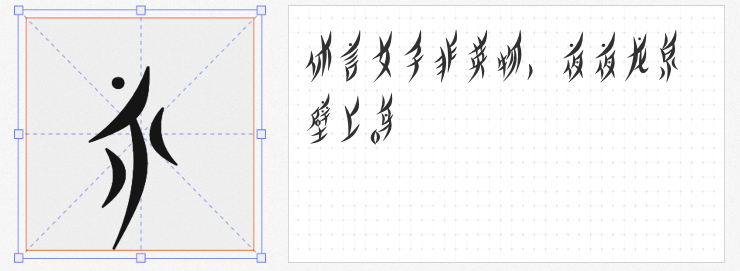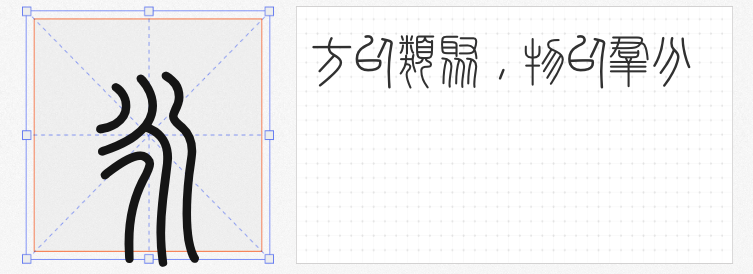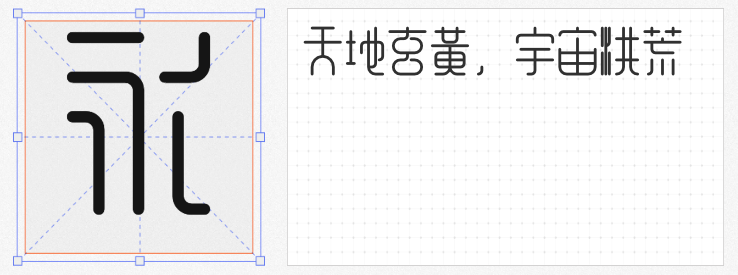
1. 余繁新语 Bold
这款字体以小篆为原型进行几何化重构,将婉转流畅的曲线转化为棱角分明的块面结构,粗细统一的笔画与夸张的负形切割形成强烈视觉张力。其“简而不失古韵”的设计哲学,既保留了篆书的仪式感,又通过简化结构适配现代排版需求。在电商促销海报中,它能以标题形式瞬间聚焦视线;在品牌标志设计中,其独特的文化符号属性更能传递历史厚重感,成为连接传统与当代的视觉桥梁。
2. 峄山碑篆体
通过高精度路径临摹技术,这款字体完整复现了秦代《峄山碑》的刀刻韵味,同时修复了千年风化导致的笔画残缺,让每个字符都呈现出金石铿锵的质感。设计团队以《说文解字》为部首规范基准,创造性地将篆书结构系统化,使非常用字也能保持统一的风格语言。在文化展览主视觉、国风产品包装等场景中,其严谨的考古级复刻精度,能为设计注入令人信服的历史真实感。
3. 也字工厂柳叶体
作为全球首款免费商用女书字体,也字工厂柳叶体以纤细飘逸的曲线重构女性专属文字符号,笔画如柳叶轻拂,既保留了原始女书“斜体弧形”的书写特征,又通过标准化处理提升多字符排版的和谐度。在女性主题公益海报、文创产品设计中,其独特的文化隐喻属性,能自然引发关于性别平等的社会思考,赋予设计超越视觉层面的精神价值。
4. 庞门正道轻松体
这款字体通过夸张的笔画圆角处理与重心上移设计,塑造出蠢萌可爱的视觉性格。其15°倾斜的横画与不规则的笔画粗细变化,为文字注入动态生命力,特别适合宠物品牌、儿童教育的视觉传达。在社交媒体表情包、幼儿绘本设计等场景中,轻松体凭借天然的亲和力,能有效拉近与受众的情感距离,实现信息的高效传递。